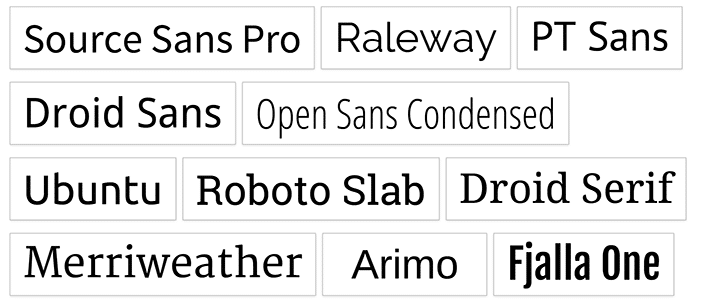
Web フォントについて知っておくべきこと
タイポグラフィは、Web デザイン作業の基本要素です。 私たちがクライアントのためにウェブサイトをデザインするために雇われた理由は、クライアントがユーザーに役立つコンテンツを提供する体験を提供できるようにするためです. しっかりとしたタイポグラフィのベースを持つことは、ユーザーが効果的に消費できる方法でコンテンツを表示するのに役立ちます. ウェブサイトには他にも多くのデザイン要素があるかもしれませんが、コンテンツが主な考慮事項であり、デザイナーとして、タイポグラフィの選択と使用によりプロジェクトを強化することが私たちの仕事です.
タイポグラフィの基本
フォントと書体
タイポグラフィの議論に入る前に、「フォント」と「書体」という用語について見ていきましょう。 書体とは、印刷上の記号と文字のセットを指します。文字、数字、および Web サイトに単語を配置するための任意の文字です。 それはアルファベットのデザインであり、基本的にそのスタイルを構成する文字の形です. Helvetica について言及するときは、書体について言及しています。
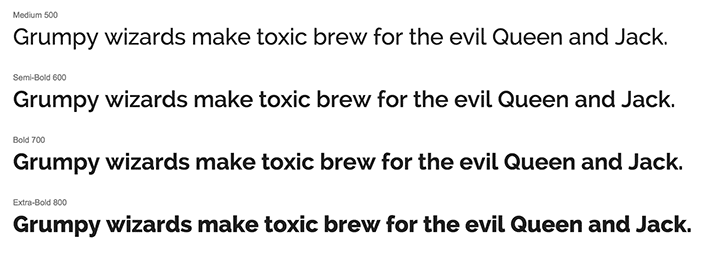
フォントは書体内の完全な文字セットとして定義され、多くの場合、特定のサイズとスタイルを参照します。 Helvetica Bold 10 ポイントは、フォントを参照する方法です。 フォントは、書体内のすべての文字とグリフを含むファイルに固有です。
この「フォント vs 書体」という素晴らしい議論は、仲間のデザイナーとの素晴らしい会話になります。 タイプにこだわる人は皆、書体について話していますが、「Web フォント」は会話で最もよく使われています。
フォント分類
世界中で利用可能な多くの書体に出くわしたら、それらがどのように分類されているかを理解する必要があります。 最も一般的な方法は、技術的なスタイル (セリフ、サンセリフ、スクリプト、ディスプレイなど) によって分類することです。書体は、プロポーショナルやモノスペースなどの他の仕様によっても分類されます。 ソースによっては、非常に具体的なものになる場合があります。
Web セーフ タイポグラフィの歴史
Web の黎明期には、非常に限定的な Web セーフ オプションにとらわれていました。 デザイナーが意図したフォントをユーザーが見るには、そのフォントがコンピューターで利用可能である必要がありました。 古いサイトのスタイルシートを開くと、Arial、Georgia、Times New Roman、Trebuchet MS、Verdana が見つかる可能性があります。 これらは、ユーザーのマシンで使用される可能性が最も高いフォントであり、大多数のユーザーが Web サイトを意図したとおりに表示できるため、「Web セーフ」であると見なされました。
しばらくの間 Web サイトをデザインしたことがある場合、または長い間 Web サーファーである場合は、タイポグラフィーのオプションが限られていた時代を覚えているでしょう。 Web サーフィンをしていると、同じ 5 つの書体を何度も目にするようになったのは、それほど昔のことではありません。 他の Web セーフ オプションがないと物事は退屈に見え始め、これらの書体は Web に最適ではないと主張する人もいるかもしれません (結局のところ、それらは印刷物から生まれました)。 しかし、Web が進化するにつれて、より多くのタイプ オプションが利用できるようになりました。
ウェブフォントとは?
タイポグラフィは非常に重要であるため、大きな進歩があったことを祝う時が来ました。 私たちは非常に多くの書体を自由に使用できるため、かつて制限されていた同じ古い Web セーフ フォントに依存する必要がなくなり、ユーザーにとって最適なものを選択できるようになりました。
Web フォントは、Web セーフ フォントのようにユーザーのシステムにプリインストールされていません。 ユーザーが自分のマシンに目的のフォントを持っていることに頼る必要はありません。 これらは含まれているソースから取得されるため、すべてのユーザーが定義されたフォントを表示できます。 これらのフォントは、Web ページのレンダリング中にブラウザーによってダウンロードされ、テキストに適用されます。
Webフォントの使い方
@font-face ルール
この広く支持されているルールにより、サーバーからフォントをダウンロードしたり、それらをホストしたりできるため、Web ページでフォントを使用できます。 スタイルシートで@font-faceルールを宣言することにより、書体の名前、場所、およびフォントの太さを指定できます。
この例は、Open Sans Regular を追加する方法を示しています。 ソースは、Web サイト プロジェクトに含まれている fonts フォルダーであることがわかります。
[/css]上記の宣言により、使用できるようにフォントが追加されます。 実際に表示するにはどうすればよいでしょうか。
[/css]フォントの名前が「Open Sans Regular」に設定されていることがわかります。 これは、何らかの理由でフォントが読み込まれない場合に備えて、フォールバック フォントと共に、CSS フォント スタックで参照されるフォント名です。 ほとんどの場合、フォントは問題なく読み込まれますが、念のためにフォールバックを含めることをお勧めします。
ほとんどのフォントには他のファミリがあり、一部のフォントは他のファミリより多いことに注意してください。 それらを利用するには、 @font-faceルールでそれぞれを含めるようにしてください。
フォーマットと Web フォント
必要なフォーマットが複数ある場合は、Web フォントについてもう少し詳しく見ていきましょう。 これらのフォントは自己ホスト型で、サーバー上の「fonts」というフォルダーに保存されます。 最後の例からいくつかの新しい行が追加されていることに気付くでしょう。
[/css].eot、.woff、.ttf、.truetype、SVG などのさまざまな形式を含める必要があるのには理由があります。 さまざまなブラウザーがさまざまなフォント形式をサポートしているため、基本をカバーし、さまざまなブラウザーが必要とするすべてのものを提供する必要があります。
フォントホスティング
Web フォントを使用する場合、デザインでレンダリングできるように、スタイルシートにはフォント自体が必要です。 このため、フォント ファイルをどこかにホストする必要があります。 フォントを格納する場所には 2 つのオプションがあります。 フォントをホストするサービスを使用するか、実際のフォント ファイルを自己ホストすることができます。 それは本当にプロジェクトに依存し、それぞれに独自の利点があります。
自己ホスト型か Typekit のようなフォント サービスを使用したホスティング型かにかかわらず、どのアプローチを採用するかによって、CSS の外観が異なります。 キットはその名の通り Typekit で作成されます。 これらには、使用するすべてのフォントが含まれています。 これらのファイルを参照するには、Javascript スニペットを HTML ドキュメントのヘッドに追加します。 これにより、正しい@font-faceルールをロードできます。
ホスティング サービス プロバイダー
言及しきれないほど多くのホスティング サービス プロバイダーがありますが、TypeKit、Fonts.com、H&Co (Hoefler and Company) はいくつかのオプションです。 基本的に、フォントはサーバー上にあり、所有しているアカウントの種類に基づいて自由に使用できます。
このアプローチには、次のような利点があります。
- 一般に、これらのプロバイダはタイポグラフィ ビジネスに携わっているため、高品質のフォントを幅広く取り揃えています。
- フォントの使用とインストールは簡単です。
- デザイン プロセス中に書体を変更したり、全体的な変更を加えたりするのは簡単です。
- これらはサードパーティのファイルであるため、ユーザーが簡単にキャッシュできます。
- HTTP リクエストが少ないほど、パフォーマンスが向上します
新しいフォントをサイトに追加するのはとても簡単です。 たとえば、Fonts.com では、プレミアム プランのメンバーシップで 3 つの異なる公開オプションを提供しています。 提供されたスタイルシートにリンクする javascript (Typekit も含む) と非 javascript オプションの両方があり、自己ホスト型オプションもあります。 何を選択するかによって、CSS の外観が異なります。
使用上の考慮事項
ホストされたフォントを使用すると、少ないほど多くのことができます。 あまり多く使用しないことが重要です。そうしないと、パフォーマンスの問題が発生する可能性があります。 同じフォントの複数のウェイトは追加セットと見なされるため、基本的に別のフォントをロードしています。 必要なものだけを含めることをお勧めします。
Web フォントの優れたソースを次に示します。
- タイプキット
独自の Web フォントを作成する
万一、完璧なフォントが見つからない場合は、いつでも独自のフォントを作成できます。 Font Squirrel は、任意のフォントを埋め込み用の Web ファイルのキットに変換する Web フォント ジェネレーターを提供します。 これらをホストする必要があることに注意してください。 詳細については、Font Squirrel Web フォント ジェネレーターをご覧ください。 独自のフォントを作成する場合、そのフォントを使用する権利を持っていることが重要です。
Web フォントは、次の Web プロジェクトに完璧なフォントを追加する優れた方法です。 多種多様な書体オプションと豊富な優れたソースにより、従来の Web セーフ オプションにとらわれる必要はもうありません。 使いやすく、試してみるのも楽しい Web フォントは、Web サイト プロジェクトに個性を加える優れた方法です。